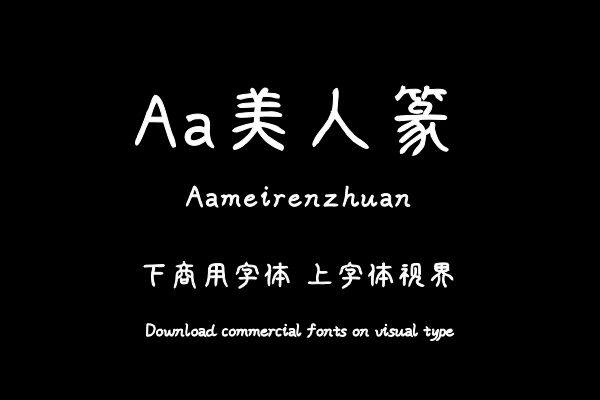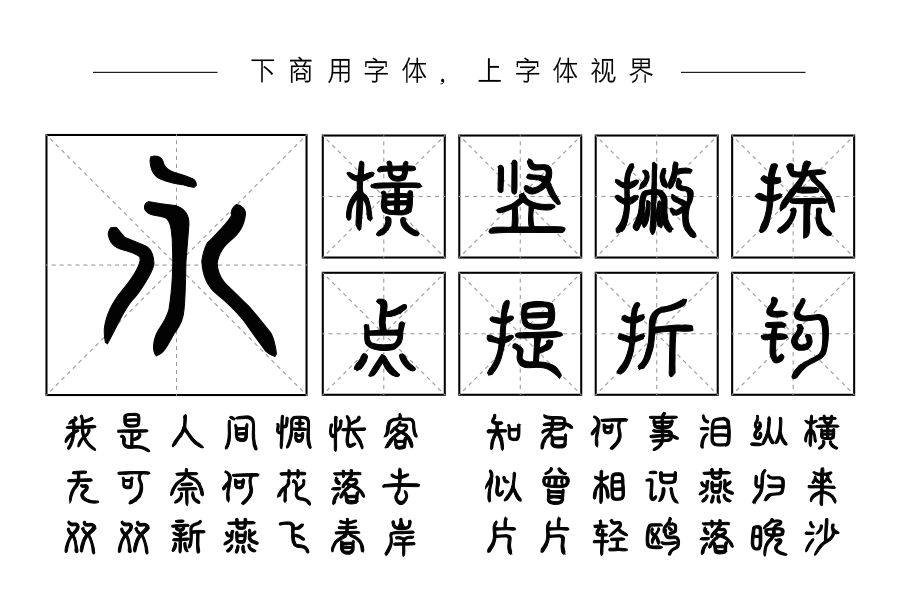
Aa美人篆是一款融合篆书特色的手写体。字形高挑,端庄雅正,整体优美、整齐,是一款稳定性高的手写字体。多作为标题字体使用,适用于古风、人文等主题。购买须知:“下载服务费”与“字体VIP”所获得字体 仅用于个人非商用, 商用请联系付费授权。本字体为电脑用字,手机没有root权限不支持直接手机换字(手机如何root,请自行百度搜索教程)。购买前请先 了解清楚后再付款 ,字体为虚拟产品无法回收 一旦购买不支持退款。